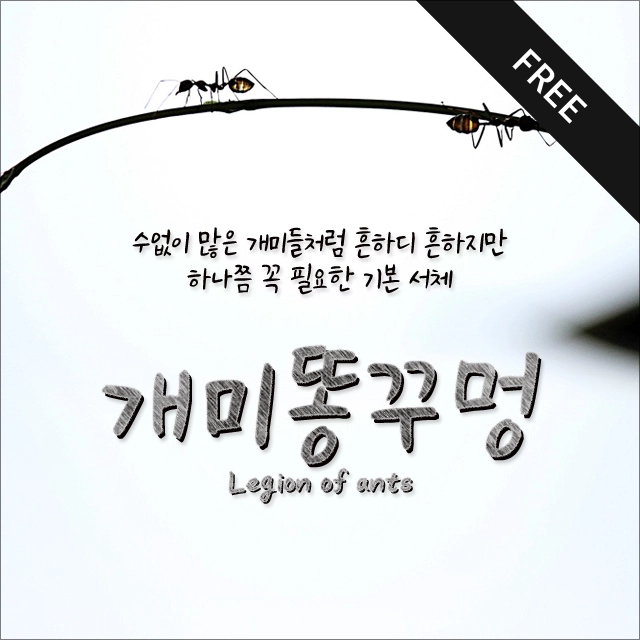
개미 똥꾸멍
땅 위를 기어다니는 수없이 많은 개미들처럼 흔하디 흔한 평범한 글씨가 필요할 때, 개미 똥꾸멍
모든 작업에 멋진 폰트가 필요한 것은 아닙니다. 때로는 땅 위를 기어다니는 수없이 많은 개미들처럼 흔하디 흔한 평범한 폰트가 필요할때가 있죠. 그럴 때를 위해 만든 감성 폰트 <개미 똥꾸멍>은 폰트를 만드는 캘리그래퍼로 불리는 상상토끼 용이 작가의 볼펜 손글씨를 기초로 해서 만들어진 폰트입니다. |